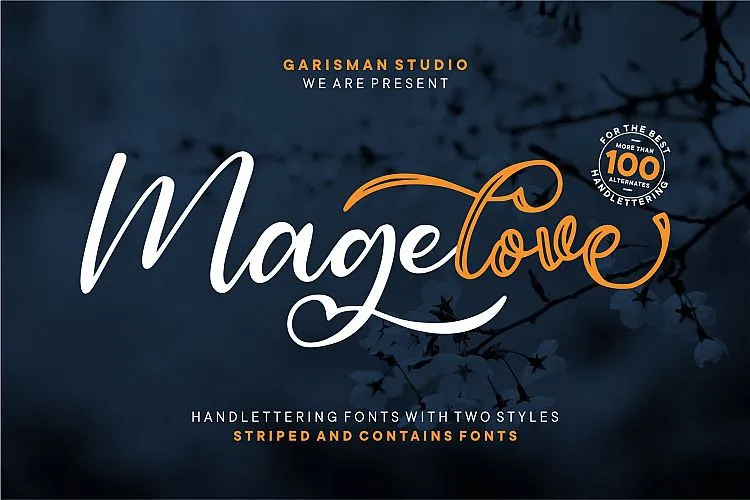
A Magelove Handlettering Font é uma elegante opção para designers que desejam dar um toque sofisticado e versátil a seus trabalhos gráficos. Com seu estilo moderno e minimalista, esta fonte de letra à mão livre captura a essência da escrita de palmo. Perfeita tanto para logotipos quanto para cartões de convite e embalagens, ou até mesmo para mensagens nas redes sociais e anúncios publicitários, o Magelove Handlettering Font é uma opção ideal. Seu estilo clássico com alternativas estilizadas oferece uma variedade infinita de ambientes para uso, fazendo dela uma escolha confiável para diversos projetos digitais e físicos. Garisman Studio desenvolveu esta fonte handlettering, que se destaca por sua naturalidade e beleza na escrita à mão livre. Uma ótima opção para quem busca uma fonte que ofereça um toque autêntico e único aos seus projetos, tornando cada projeto ainda mais especial.